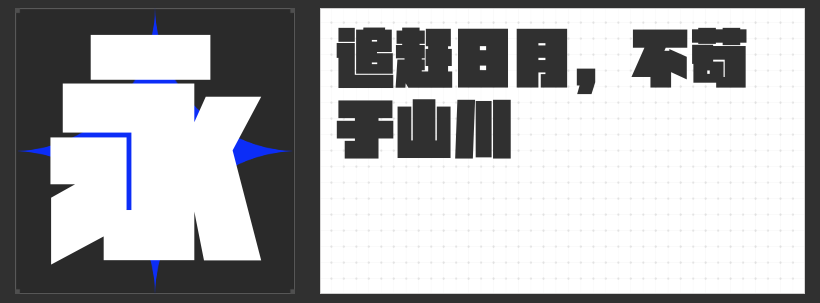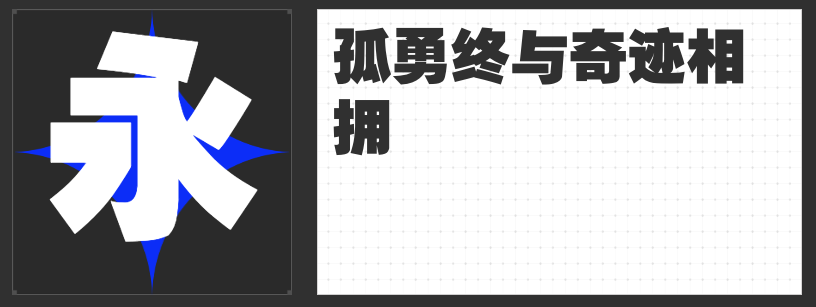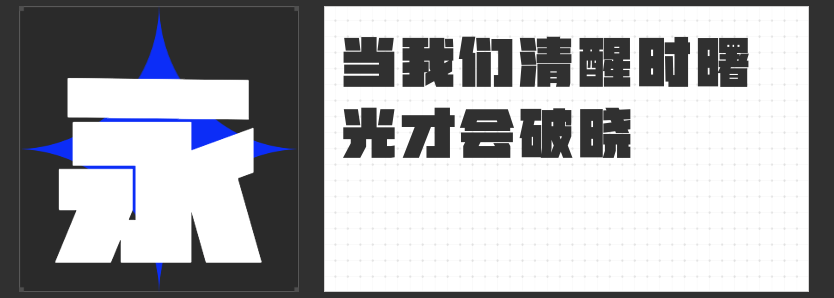
四款超粗字体推荐:以力量感重塑设计视觉秩序
在视觉传达中,超粗字体以其强烈的存在感与视觉张力,成为标题、品牌标识、海报等场景的核心元素。它们不仅能快速聚焦注意力,更通过形态语言传递出坚定、权威或先锋的态度。以下四款超粗字体,以独特的结构设计与风格语言,为设计注入不容忽视的视觉能量。
一、励字开拓者简 超级黑
这款字体以方正字型为基底,中宫舒展,重心沉稳,构建出均衡的视觉框架。其笔画摒弃曲线,采用纯粹的直线切割,横竖笔画棱角分明,起笔与收笔以平切收尾,内部空间通过几何分割形成均匀的负形,整体如精密仪器般规整。部分钩笔画被简化为直线,撇、捺、点则以竖直形态呈现,强化了镜像对称的视觉效果。这种设计语言使其在科技、工业、建筑等主题的设计中,能精准传递理性与秩序感。
二、励字暴风简 超级黑
基于现代黑体骨架,这款字体通过笔画粗细的梯形变化与不规则分布,赋予传统黑体以动态生命力。横竖笔画由粗至细渐变,形成视觉上的推进感;撇、捺、点融入更多梯形元素,硬朗的线条与开放的结构打破常规,营造出冲突与平衡并存的现代文艺气质。其设计既保留了黑体的稳重,又通过形态创新传递出先锋态度,适合文化、艺术、时尚等领域的视觉表达。
三、高手兵克坚黑体
作为一款无弧度创意超粗黑体,其设计哲学聚焦于“纯粹的力量”。笔画以直线为主,粗细均匀,无任何装饰性衬线,字面接近正方形,结构紧凑而稳定。超黑的字重使其在远距离或小尺寸下仍能保持清晰可读性,成为标题、LOGO等场景的理想选择。其极简风格既能独立成为视觉焦点,也可与复杂元素形成对比,强化设计层次。
四、励字超黑简繁
这款字体以超粗笔画与严谨结构诠释“稳重”二字。字形端庄,字面方正,笔画粗壮有力且无尖角,撇捺收笔圆润,整体呈现朴素大方的气质。无衬线设计使其在传统与现代语境中均能游刃有余,既适用于文化类设计的庄重表达,也可通过与其他字体的对比,为商业设计增添厚重感。
四款字体虽同属超粗类别,却以差异化设计满足多元需求。它们以形态语言重构视觉权重,让设计在信息洪流中脱颖而出。